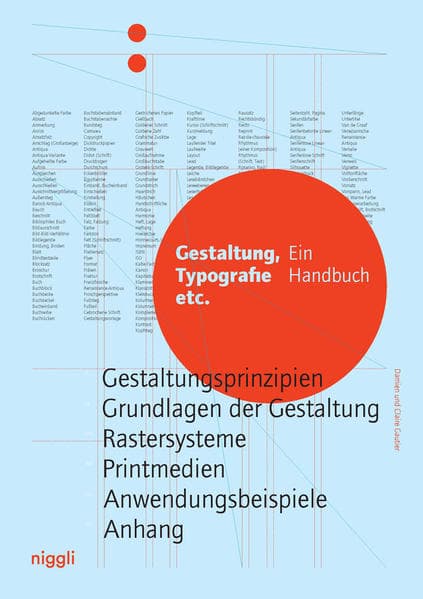
Gestaltung, Typografie etc
Ein Handbuch
Warum sieht eine Zeitung anders aus als eine Zeitschrift oder ein Buch? Welche Auswirkungen hat die Verwendung einer bestimmten Schrift, welche die eines bestimmten Rasters? Und warum wirkt das eine Layout ausgesprochen passend und überzeugt und ein anderes eindeutig falsch? Mittels Abbildungen, Zeichnungen und erläuternden Texten werden in diesem umfassenden Handbuch und Nachschlagewerk sämtliche Grundlagen und Fachbegriffe erklärt, deren Kenntnis an der Schnittstelle von Gestaltung und Produktion von Printmedien unumgänglich ist. Vom Aufbau einer Seite über die richtige Verwendung von Farben und Schriften bis hin zu Spaltenbreite und Zeilenlauf: Reich bebildert und mit zahlreichen Beispielen internationaler Druckerzeugnisse behandelt "Gestaltung, Typografie etc." sämtliche Aspekte guter Buch-, Plakat- und Anzeigengestaltung.